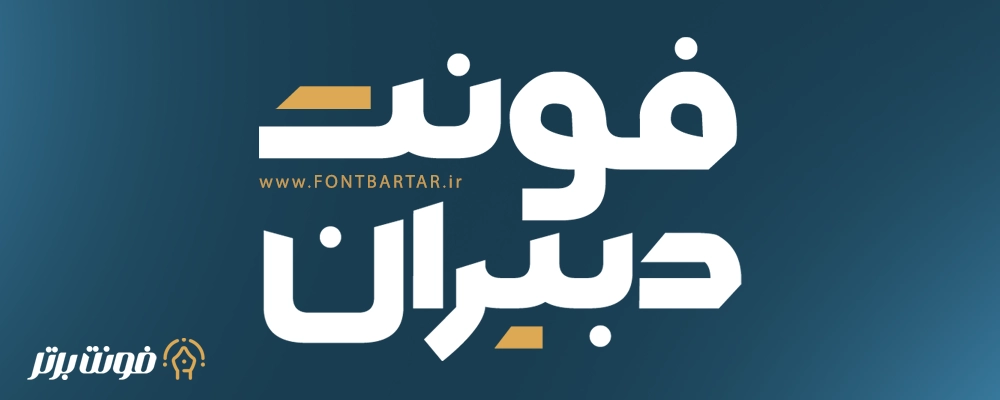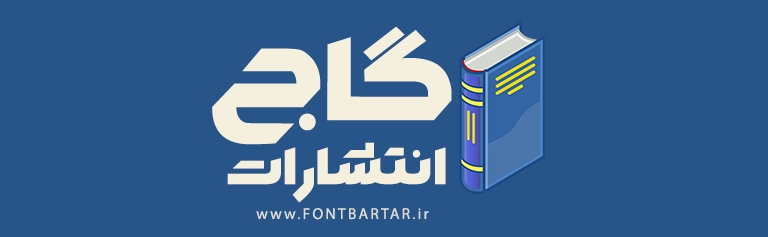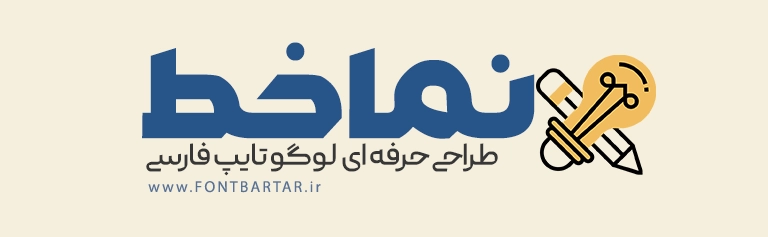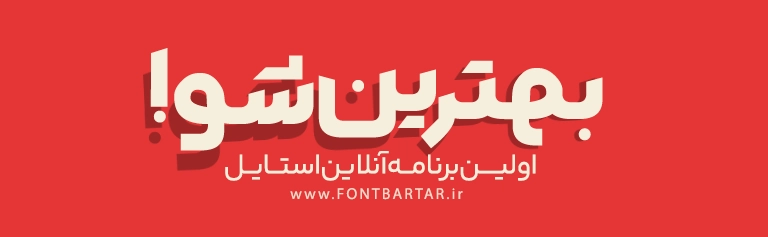
فونت جدید دبیران
Dabiran Font
فونت دبیران – ترکیب خوانایی و جسارت در طراحی فارسی
فونت جدید دبیران یکی از جدیدترین و خلاقانه‌ترین فونت‌ های فارسی است که توسط مجموعه‌ی فونت برتر طراحی و عرضه شده است، فونت جدید فارسی با ضخامت متعادل، ساختار مدرن و انحناهای نرم خود، مناسب طراحانی است که به دنبال یک فونت حرفه‌ای و متمایز برای پروژه‌های خود هستند.
اگر به دنبال فونتی هستید که هم قدرت بصری بالا داشته باشد و هم خوانایی‌اش در سایزهای مختلف حفظ شود، فونت دبیران انتخابی هوشمندانه است.
🎨 ویژگی‌ های فونت دبیران
• طراحی مدرن و حرفه‌ای بر پایه اصول تایپوگرافی فارسی
• مناسب برای استفاده در تیتر، لوگوتایپ، پوستر و کاورهای تبلیغاتی
• هماهنگی کامل بین حروف فارسی و انگلیسی
• وزن متعادل برای استفاده در چاپ و وب
💼 کاربردهای فونت دبیران
• طراحی لوگوتایپ‌های فارسی مدرن
• ساخت پوسترهای تبلیغاتی و فرهنگی
• تایپوگرافی در شبکه‌های اجتماعی
• طراحی بنر و رابط کاربری وب (UI)
• استفاده در برندینگ و طراحی سازمانی
1. فونت دبیران برای چه نوع طراحی مناسب است؟
فونت دبیران برای طراحی لوگوتایپ، پوستر، بنر و تیترهای گرافیکی عالی است.